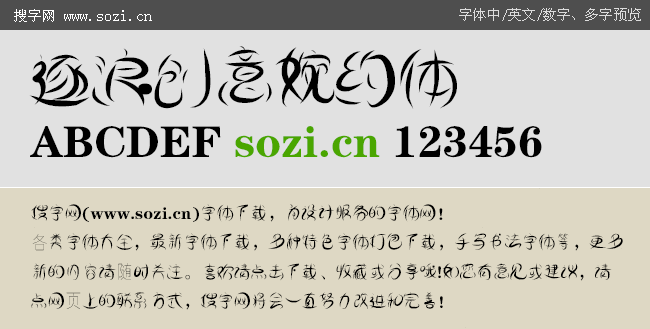
逐浪創(chuàng)意婉約體
搜字網(wǎng)提供一款逐浪創(chuàng)意婉約體中文藝術(shù)字體下載,逐浪創(chuàng)意婉約體是一種基于現(xiàn)代漢字簡體設(shè)計(jì)的字體,字體設(shè)計(jì)原則力求符合當(dāng)代人的審美規(guī)則,整體效果十分出色,適合應(yīng)用于廣告設(shè)計(jì)、名片設(shè)計(jì)、包裝印刷、產(chǎn)品設(shè)計(jì)等應(yīng)用。(逐浪字庫如需商用授權(quán),請聯(lián)系:0791-86161900 QQ:404655890)